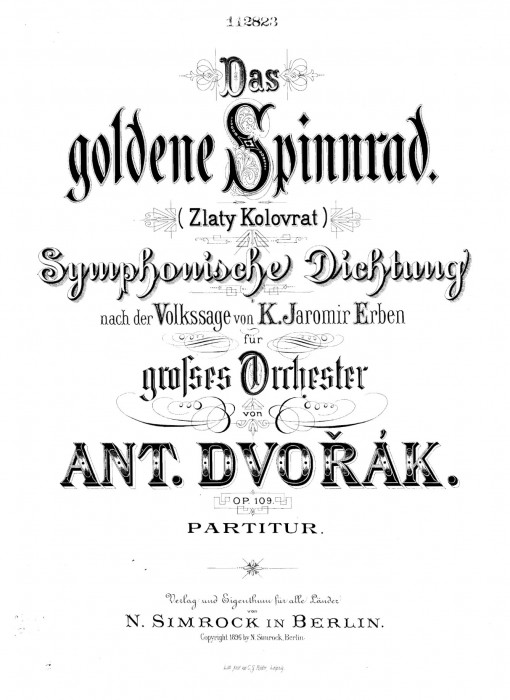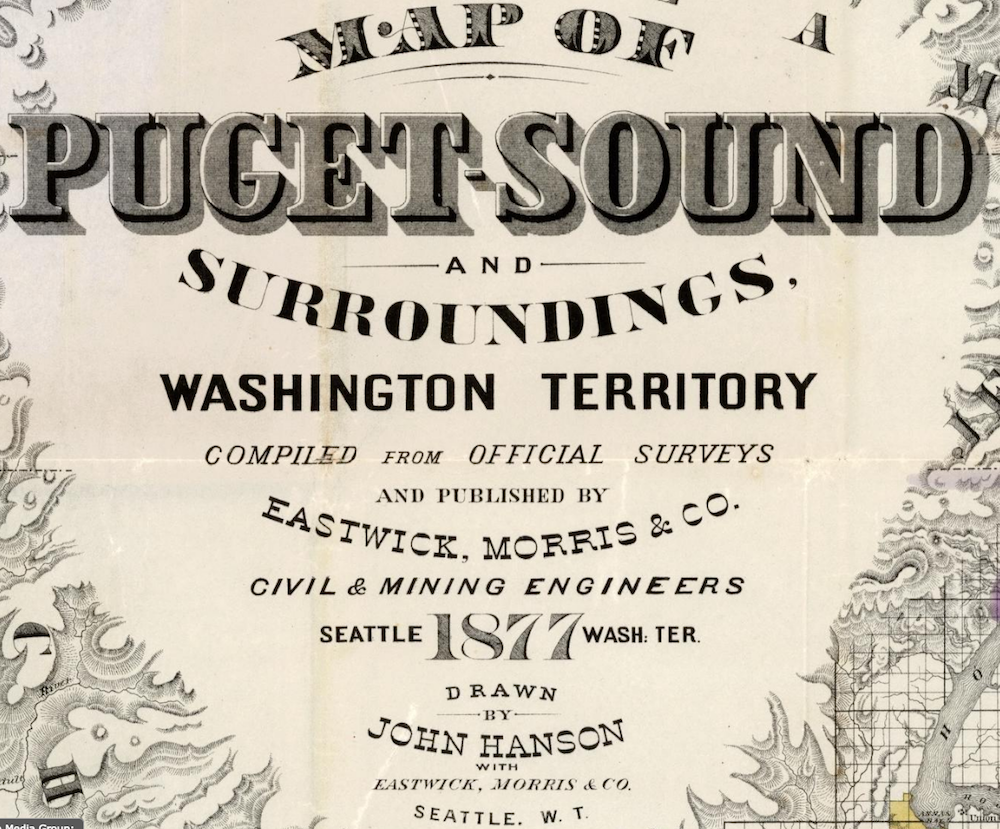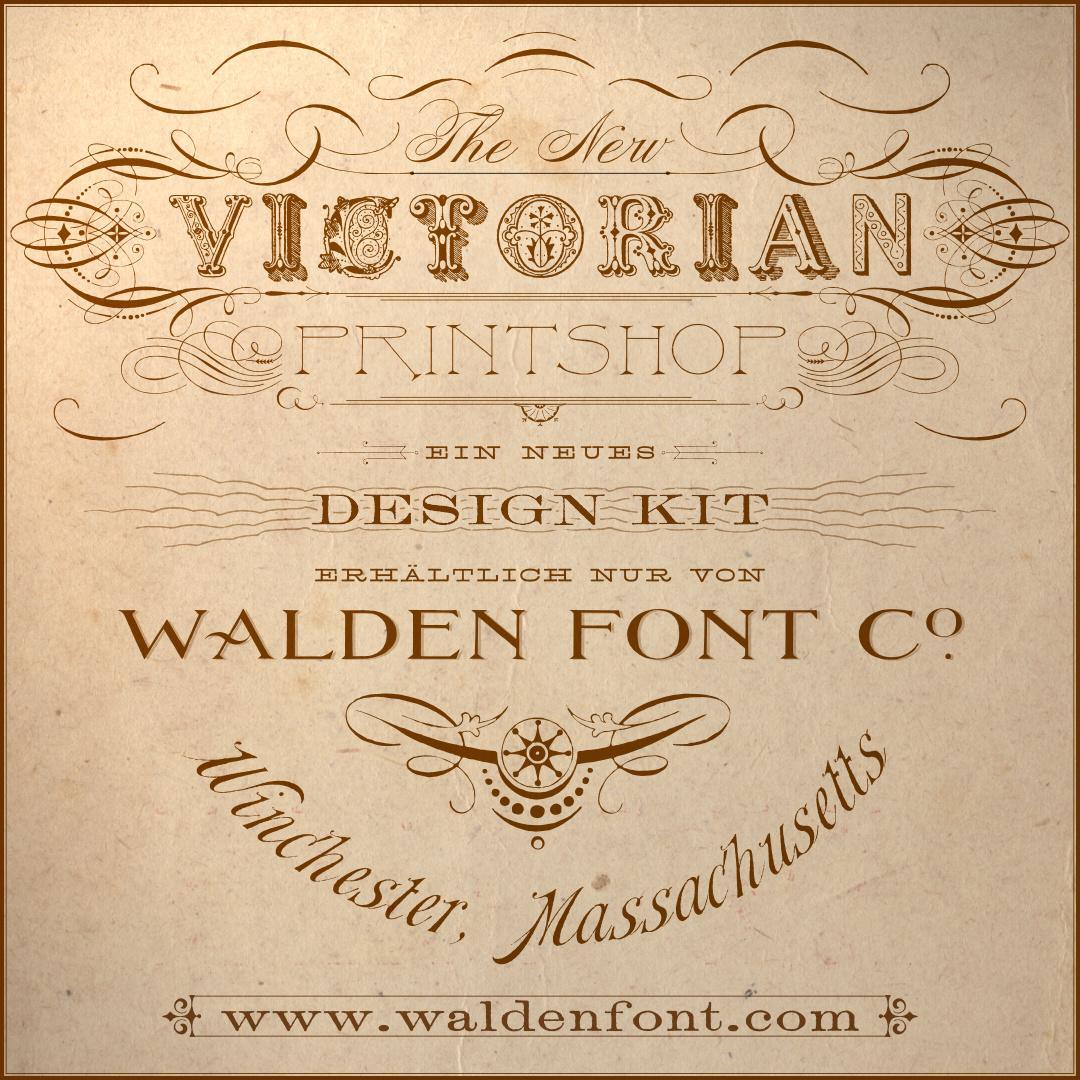
Hast Du schon archive.org geplündert?
Und noch viel mehr Auswahl: https://archive.org/search.php?query=subject%3A"Type+and+type-founding+--+United+States+--+Specimens"
Bei Büchern vor 1950 schaue ich immer zuerst bei archive.org nach, ob es das bereits als Digitalisat gibt. Abhängig von der scannenden Institution können die wirklich hochwertige Scans haben.
Gerade bei Reddit gesehen. Die Schriften sind für mich gerade richtig. Ernst, aber dekorativ. In meiner augenblicklichen Stimmung schwebt mir des öfteren vor, ein Gruselkabinett für Erwachsene aufzumachen - Mahnbriefe, eine Tür hinter der ein Polizist steht und sagt "Es tut mir leid." Da gehört so was rein.
Manchmal denke ich angesichts abenteuerlicher antiquarischer Schriftmischungen ja: »Aha, das war halt noch übrig.«
Aber wenn es – wie hier – handgezeichnet (bzw. -gestochen?) ist, dann ahne ich: Das war Absicht. Mutig.
Oh, die Verwendung möglichst vieler verschiedener Schriften war in Victorianischen Zeiten de rigeur!  Das ging einher mit der Ornamentiersucht die sich in allen gestalteten Objekten niederschlug. Selbst die Heimausstattung und die Garderobe waren davon betroffen. Ein Victorianisches Zimmer war nicht komplett, solange irgendwo auch nur ein Quadratzoll Platz war.
Das war ja bei Notenverlagen auch sehr üblich, siehe das Beispiel unten. Wir hatten einen ganzen Schrank voll davon. Ich finde sowas ja total gut. Irgendwann wenn ich mal zu viel Zeit habe dann versuche ich mal mein Türschild für die Uni so nachzubauen. Darauf warte ich schon seit Jahren! :hammer:
Aber genau so habe ich mir das tatsächlich vorgestellt. Ich schaue mir den New Victorian Printshop tatsächlich einmal näher an.